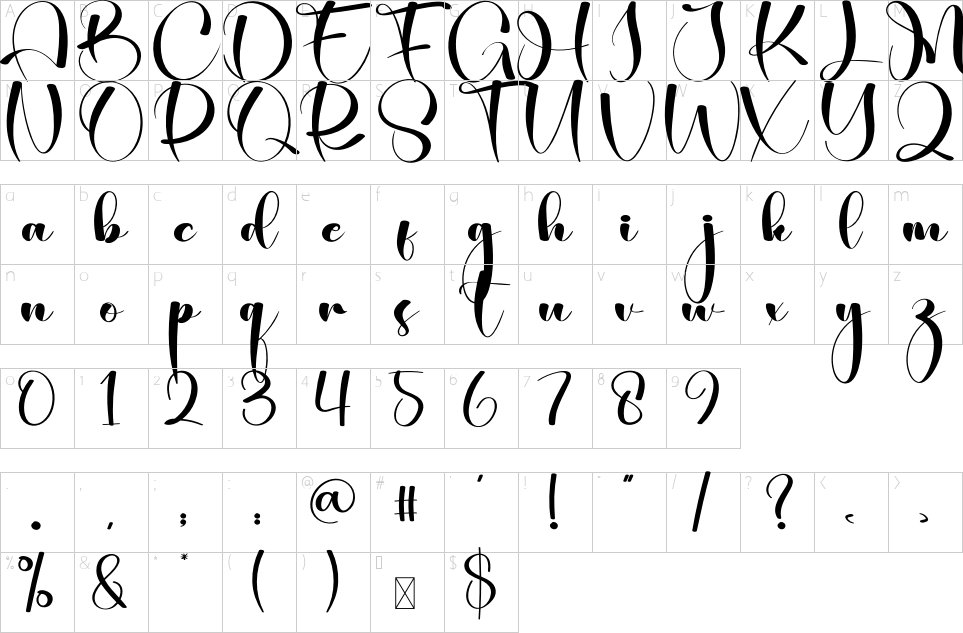
Autumn Font é uma fonte grata que se destaca pela sua paleta de cores acolhedoras e textura suave, criada especialmente para criar experiências de leitura confortáveis. Suas linhas são legíveis e adequadas para uso em diversas aplicações, desde materiais gráficos até páginas web. Esta fonte foi projetada por scratchones e já foi baixada 163 vezes. Com uma aparência amigável e natural, ela combina perfeitamente com o seu estilo, fornecendo uma opção segura e agradável para quem procura uma fonte de leitura suave e harmoniosa. Sem dúvida, é um recurso indispensável para quem busca uma fonte de alta qualidade para os projetos digitais.